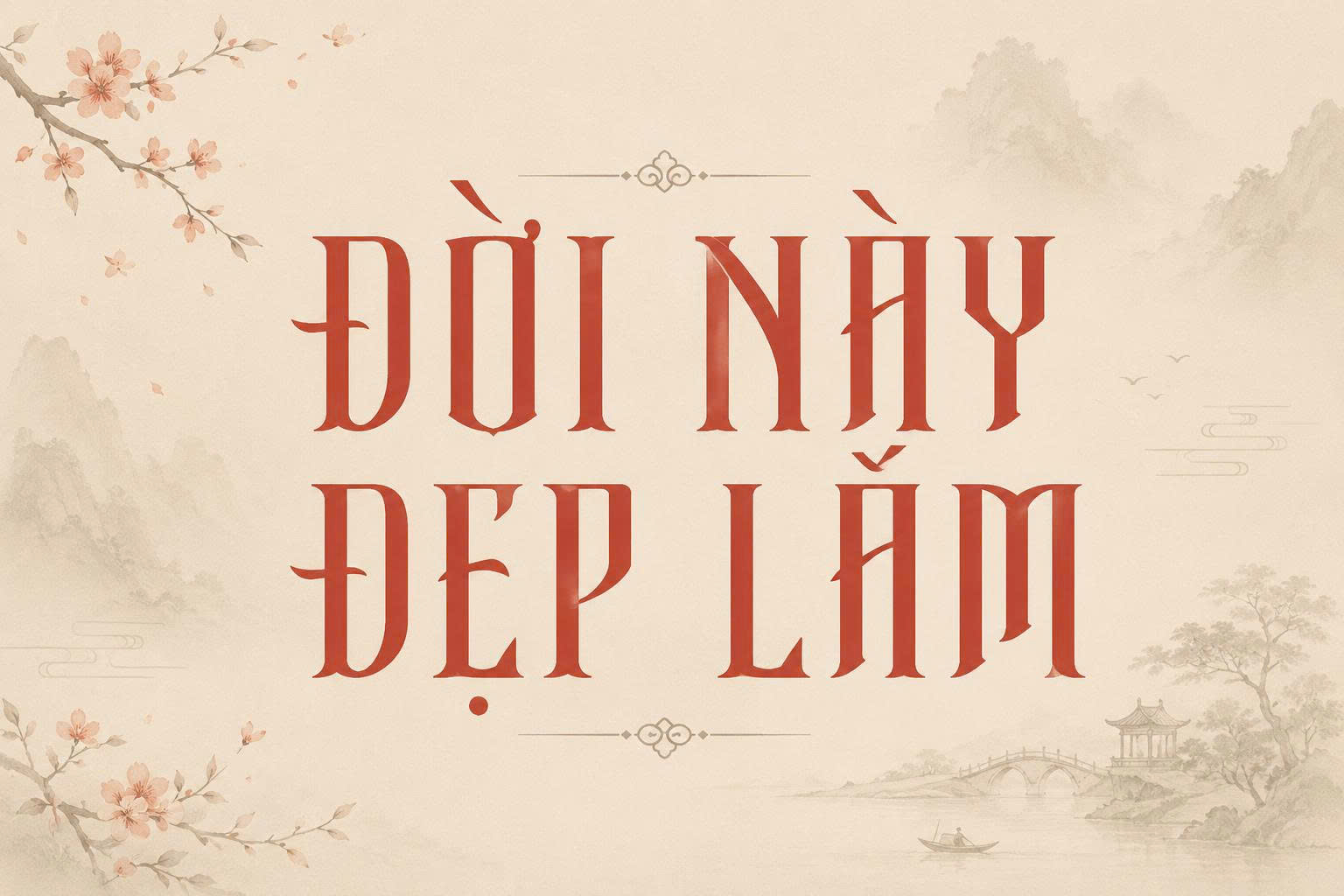
Font cổ trang Việt hóa là những bộ phông chữ mang đậm nét văn hóa truyền thống Á Đông, mô phỏng lối viết tay của các thư pháp gia hoặc các ký tự trên văn bia, mộc bản xưa. Với sự trỗi dậy của phong cách cổ phong trong đồ họa, việc tìm kiếm một bộ font chữ cổ trang Việt hóa chuẩn để thiết kế bao bì, poster phim hay làm font việt hóa edit truyện cổ trang đang trở thành nhu cầu thiết yếu. Doozypack.vn cung cấp link tải trọn bộ phông chữ hoài cổ chất lượng cao, giúp bản thiết kế của bạn toát lên vẻ đẹp tinh tế, uy nghi mà không gặp lỗi hiển thị dấu tiếng Việt.
Tại sao font chữ cổ trang Việt hóa lại được designer săn đón?
Phong cách cổ trang không chỉ là xu hướng nhất thời mà là cách thương hiệu kết nối với giá trị văn hóa và chiều sâu lịch sử.
Tái hiện không gian hoài cổ và tinh tế
Các bộ font việt hóa cổ trang sở hữu đường nét biến hóa linh hoạt, từ nét thanh mảnh thanh thoát đến nét đậm mạnh mẽ như nhát bút lông đẫm mực. Những đặc điểm này giúp bản thiết kế ngay lập tức mang hơi thở của quá khứ, phù hợp với các sản phẩm như trà, rượu, dược liệu hoặc các ấn phẩm văn hóa tâm linh.
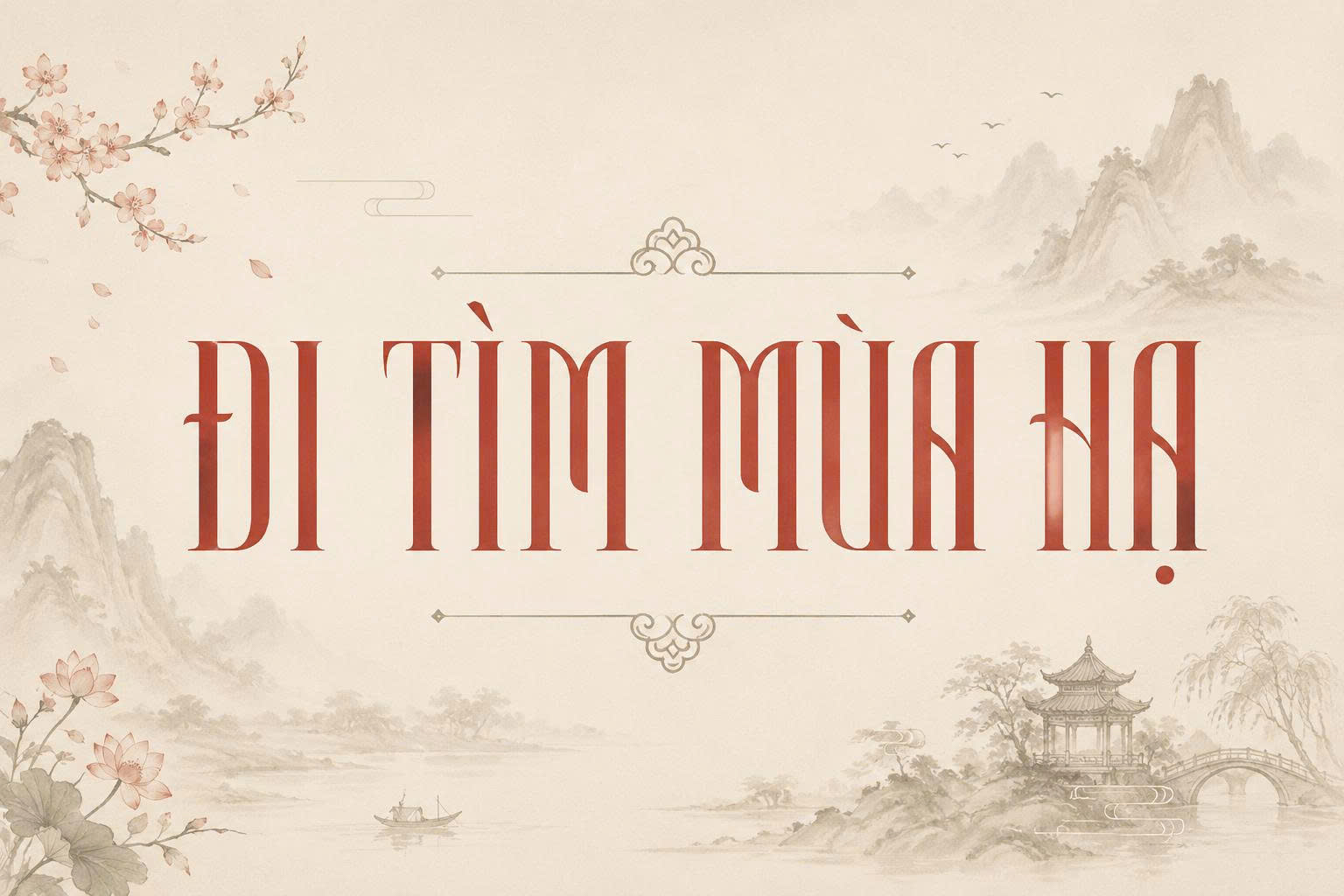
Giải quyết triệt để lỗi dấu khi soạn thảo tiếng Việt
Nỗi đau lớn nhất của các editor và designer là khi tìm được một bộ font cổ phong đẹp nhưng lại bị lỗi dấu khi gõ tiếng Việt. Bộ sưu tập font chữ việt hóa cổ trang tại Doozypack.vn đã được tinh chỉnh lại toàn bộ hệ thống dấu thanh (sắc, huyền, hỏi, ngã, nặng), đảm bảo sự cân đối về mặt thị giác và tính chuyên nghiệp cho mọi ấn phẩm.
Tổng hợp các nhóm font việt hóa cổ trang phổ biến nhất
Tùy vào mục đích sử dụng là in ấn bao bì hay edit truyện, bạn có thể lựa chọn các nhóm font sau:
- Nhóm font thư pháp (Brush Style): Mô phỏng nét bút lông phóng khoáng, có độ xước tự nhiên. Đây là lựa chọn hàng đầu để làm tiêu đề hộp quà hoặc bìa truyện kiếm hiệp.
- Nhóm font chữ triện, chữ mảnh (Elegant Style): Mang phong cách cung đình thanh lịch, nét chữ gọn gàng nhưng vẫn giữ được nét cổ kính, phù hợp cho các thương hiệu mỹ phẩm đông y hoặc trà đạo.
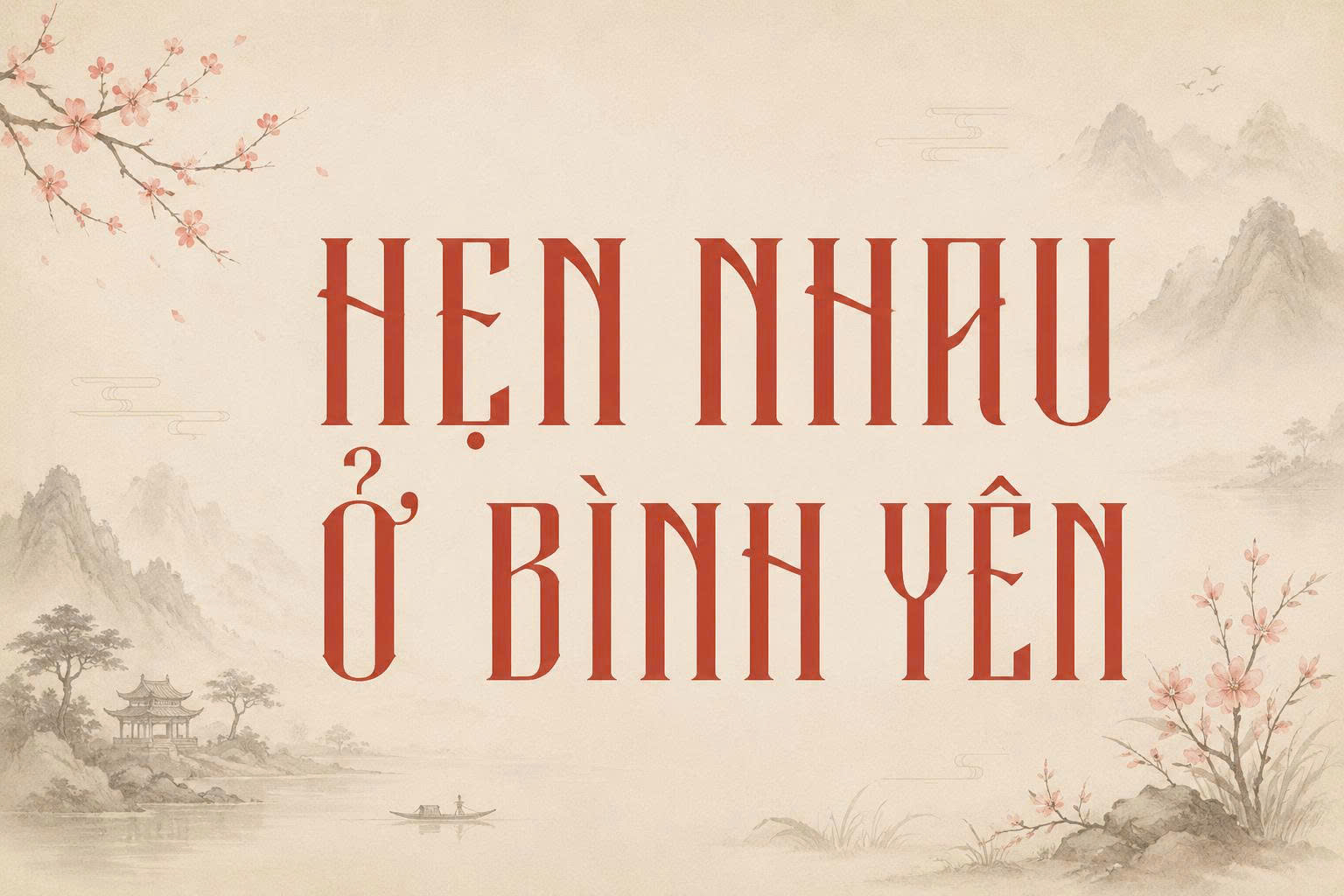
03 Ứng dụng font cổ trang trong in ấn bao bì tại Doozypack.vn
Tại Doozypack.vn, chúng tôi thường xuyên hỗ trợ khách hàng ứng dụng font việt hóa cổ trang vào sản xuất thực tế để tạo nên dấu ấn thương hiệu riêng biệt:
- Thiết kế hộp bánh Trung thu: Những tiêu đề như “Nguyệt Viên”, “Đoàn Viên” sử dụng font thư pháp cổ trang in trên nắp hộp giấy giúp nâng tầm giá trị món quà lễ hội.
- Nhãn rượu và hộp trà: Sự kết hợp giữa font cổ trang và chất liệu giấy mỹ thuật nhám tạo nên cảm giác sản phẩm truyền thống lâu đời và uy tín.
- Bao lì xì Tết: Các câu chúc xuân bằng font chữ hoài cổ in ép kim đỏ/vàng mang lại không khí Tết xưa đầy ý nghĩa.
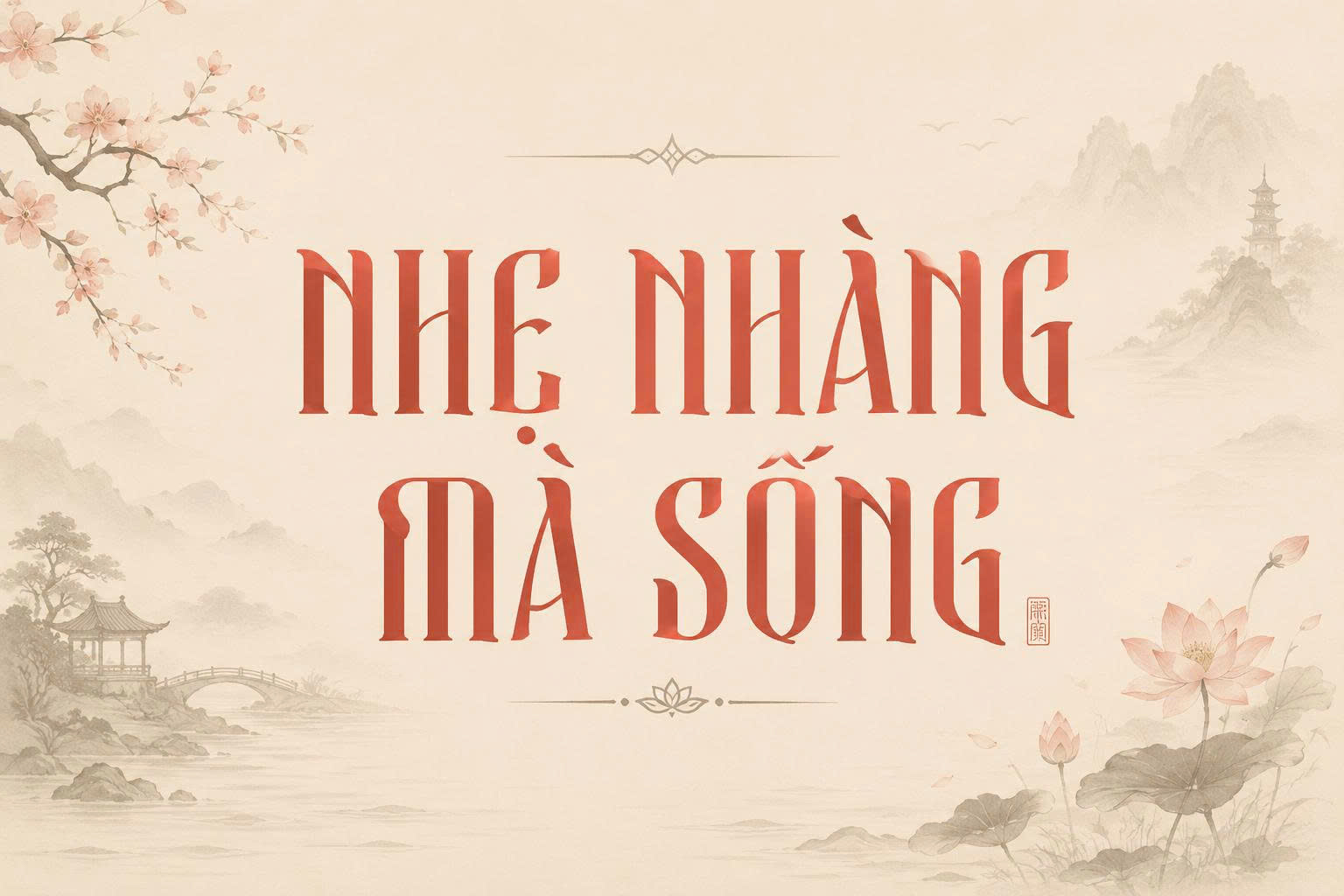
Lưu ý kỹ thuật khi sử dụng font việt hóa edit truyện cổ trang và in ấn
- Vấn đề nét mảnh khi ép kim: Một số font việt hóa edit truyện cổ trang có nét nối rất thanh mảnh. Khi đưa vào in ép kim trên hộp giấy cứng, những nét này dễ bị đứt quãng. Bạn nên kiểm tra độ dày nét chữ tối thiểu là 0.2mm trước khi làm khuôn.